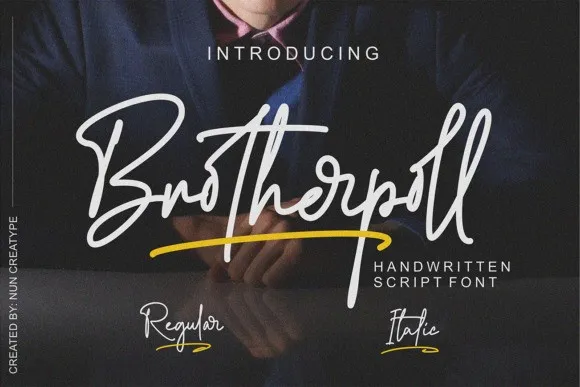
Brotherpoll Script Font – Download Grátis
A Brotherpoll Script Font é uma novidade no gênero de fuentes script, criada pela Nun Creatype. Este tipo de fonte tem a característica de estilizar a escrita à mão e permite que sua elegância seja ainda mais evidente. Ela é perfeita para criar um impacto em posts ou mensagens carregadas de emoção. A Brotherpoll Script Font vem com diferentes estilos, cada um capaz de produzir uma impressão única. Com seu traço fino e encantador, esta fonte casual-chic é ideal para personalizar logotipos, adesivos, assinaturas no Instagram e sites, sendo usada onde a criatividade e o toque pessoal são bem-vindos. Sem dúvida, essa fonte é perfeita para quem busca uma maneira elegante de expressar sua identidade visual e personalidade única em diferentes ambientes digitais.